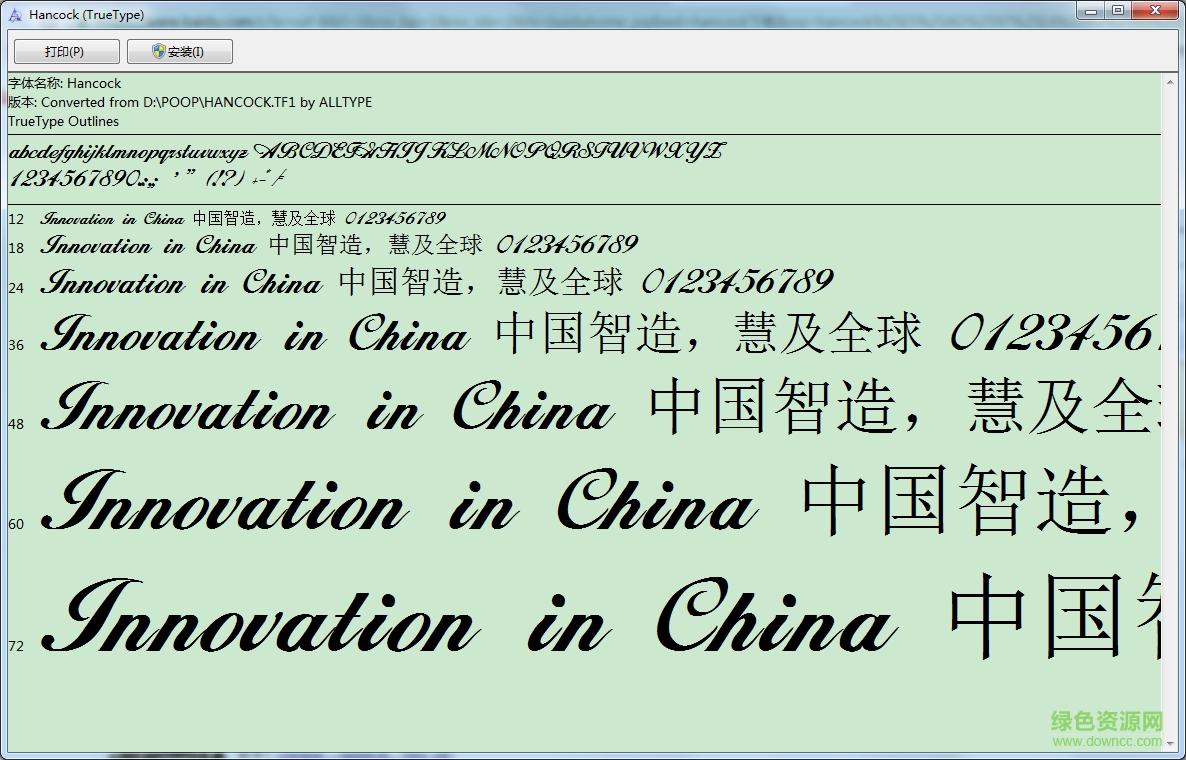
Hancock字體
Hancock是一款非常優(yōu)雅的英文字體,此款字體帶由西方復(fù)古風(fēng),字型飄逸瀟灑,外形出眾美觀,廣泛的應(yīng)用于封面設(shè)計(jì)、廣告設(shè)計(jì)、平面設(shè)計(jì)等領(lǐng)域,喜歡的朋友歡迎來綠色資源網(wǎng)下載!